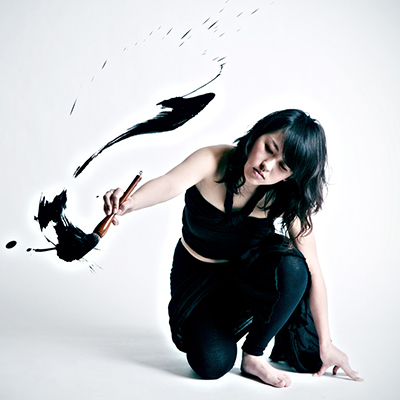
Inspiriert von „wanderlust“, dem Thema der TYPO Berlin 2017, präsentiert Aoi Yamaguchi in Zusammenarbeit mit dem Berliner Musiker Schneider TM und der eTextile-Künstlerin Mika Satomi eine interaktive, großformatige Konzept-Kalligraphie.
Die einzigartige Kunst der Kalligraphie ist Dekonstruktion und Transformation bestehender Sprachkonventionen mit dem Pinsel. Dabei erfüllt die Kalligraphin das Zeichen mit ihrer Interpretation einer Idee, die jede Performance zu einem Unikat werden lässt. Das Publikum erlebt japanische Kalligraphie und erkundet die Verbindung von Körper und Geist, während Yamaguchi mit ihrem Pinsel Strich für Strich ihr Konzept physisch sichtbar macht.
Die Bewegungen der Künstlerin werden in dieser Performance von Sensoren erfasst und in ein Signal übertragen, das die Instrumente steuert. Jede Pinselbewegung wird durch die Sensoren verstärkt, die Schneider TMs Komposition erhöhen und sie wirkmächtig modulieren. In ihrem Pulsieren werden die Zuhörer ein Teil des Stücks selbst.
** 琳瑯 (Linlow) ist ein altjapanischer Begriff für:
1. schöne Edelsteine, schöne Gedichte, Poesie;
2. den schönen Klang, der entsteht, wenn sich schöne Edelsteine berühren.
琳瑯 ist ein Zitat eines meiner Lieblingsautoren: Soseki Natsume schreibt in seinem Buch Kusamakura:「芸術家は無数の琳琅を見、無上の宝璐 (ほうろ) を知る」„Der Künstler sieht zahllose schöne Gedichte (Literatur, Komposition) und kennt den größten Schatz.“